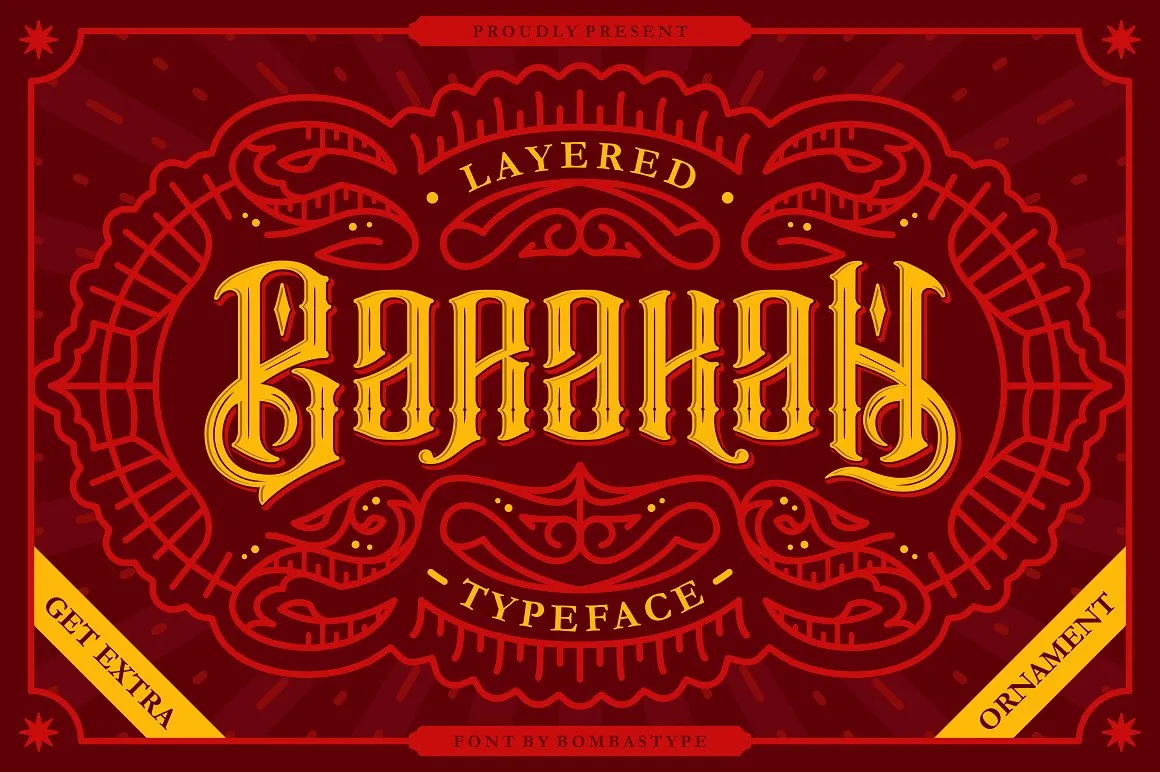
Barakah Layered Typeface – Download Grátis
Introduzimos a Barakah! Esta elegante fonte foi criada por 178-MC para a Unio | Creative Solutions. É uma fonte premium que você pode adquirir na Creativemarket, mas está disponível gratuitamente hoje para download. Uma das suas características mais interessantes é seu design multi-livrazo victoriano: Regular, Inline, Inner Shadow e Drop Shadow. Inspirada nos desenhos vintage, especialmente no design de etiquetas antigas e assinaturas vintage, a Barakah Typeface se destaca como uma opção perfeita para logotipos, panfletos, rótulos ou qualquer aplicação de design em exibição. Estamos convencidos de que sua criatividade é infinita com essa fonte.